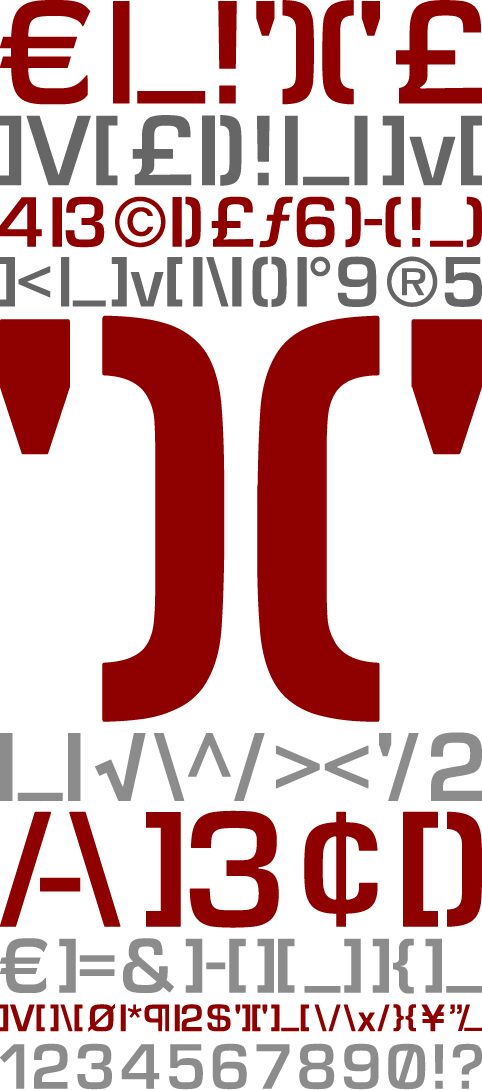
Elite Medium von Butter ist eine kostenlose Art-déco-Display-Schrift. Mit ihren kräftigen Strichen, quadratischen Kurven und scharfen Ausschnitten wirken die Buchstaben zugleich maschinell und theatralisch. Die Formen sind breit und grafisch, abgerundete Außenkanten treffen auf abrupte vertikale Schnitte – das verleiht der Schrift einen Rhythmus wie von alten Postern, statt neutraler Alltäglichkeit.
Sie eignet sich perfekt für Magazincover, Branding für Bars und Lounges, Filmtitel, Event-Plakate und Verpackungen – überall dort, wo kurze Zeilen diesen stilisierten Look zwischen 1920er-Jahren und Futurismus brauchen. Als Free-Font eignet sie sich auch hervorragend für Monogramme oder große Initialen, da die Buchstaben formstark genug sind, um auch bei knapper Verwendung Aufmerksamkeit zu erregen.
1337-Font für Internet-Geeks und Gamer